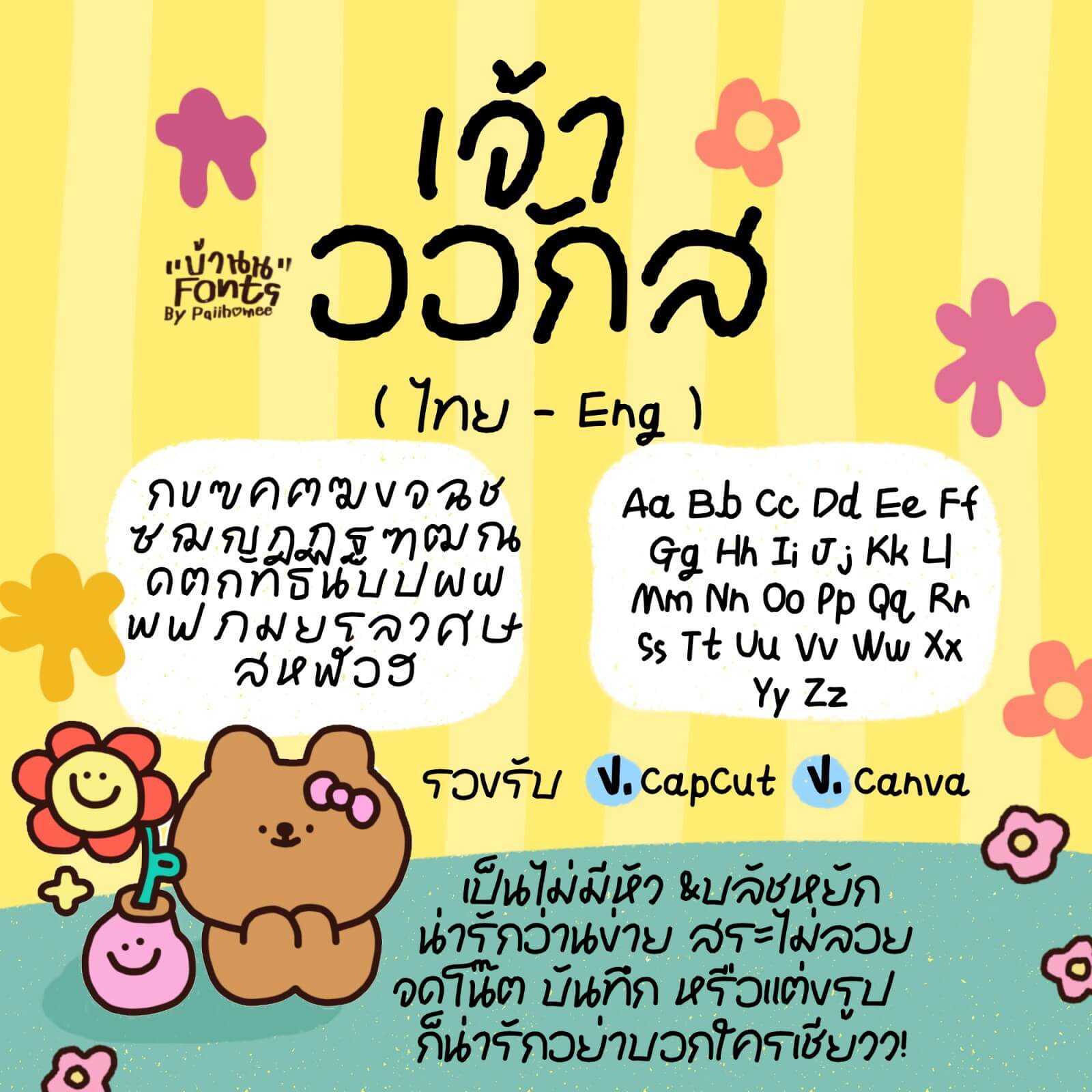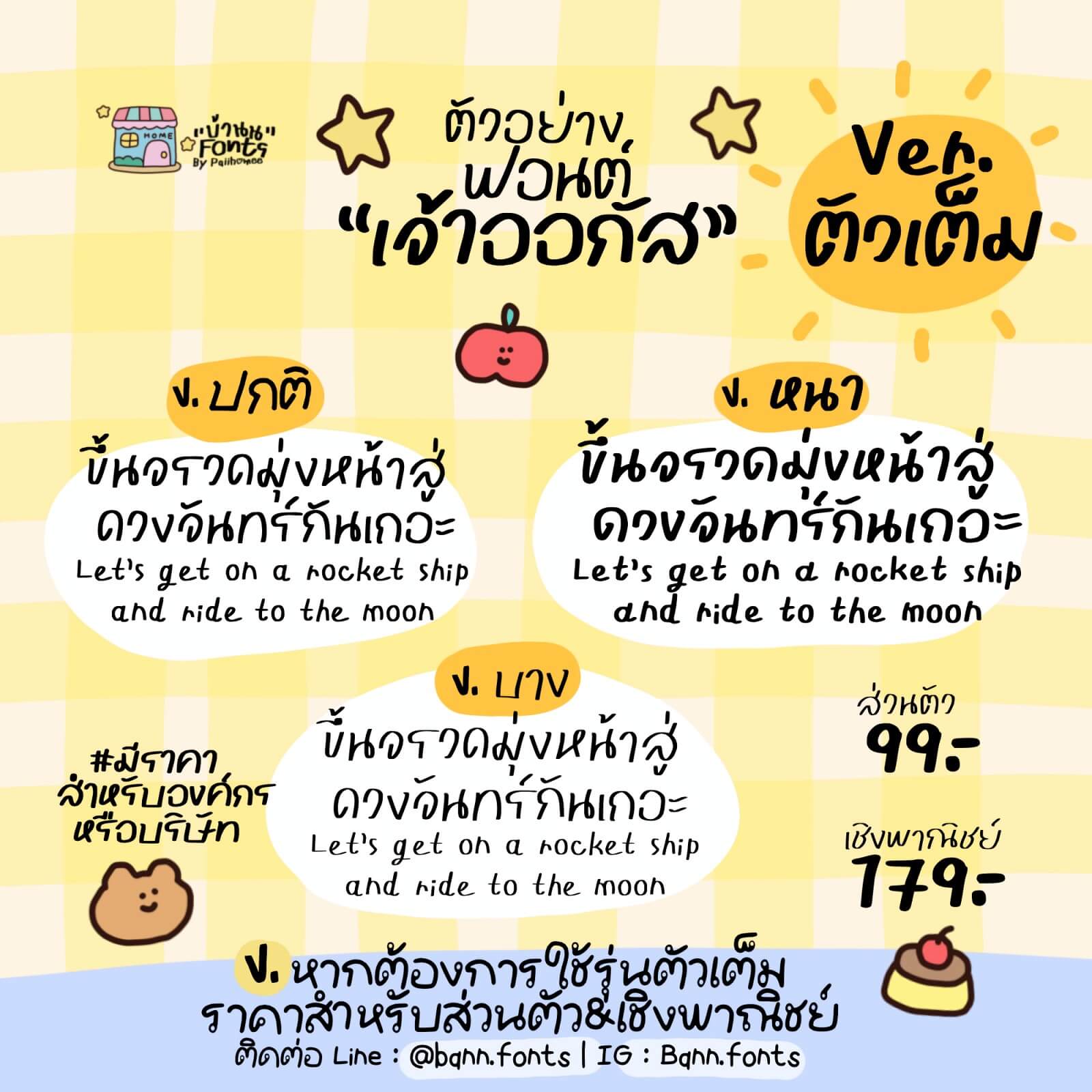
ฟอนต์เจ้าออกัส (บรัชหยัก) – แจกฟรี! ฟอนต์ไม่มีหัว เท็กซ์เจอร์หยักๆ เพิ่มความน่ารักตะมุตะมิ อ่านง่าย สระไม่ลอย ใช้งานได้ทั่วไป เช่น ทำคลิป แต่งปกรูป และอนุญาตให้สร้างผลงานแล้วหารายได้จากน้องได้เลย โหลดไว้ติดเครื่องไว้เลย แนะนำเลยค่ะ!
เวอร์ชั่นฟรี จะเป็นบรัชหยัก(พิเศษ)
ส่วนฟอนต์เวอร์ชันเต็ม จะมีทั้งหมด 3 ขนาด (เส้นบาง เส้นปกติ และ เส้นหนา)
เจ้าออกัส (JaoAugust)